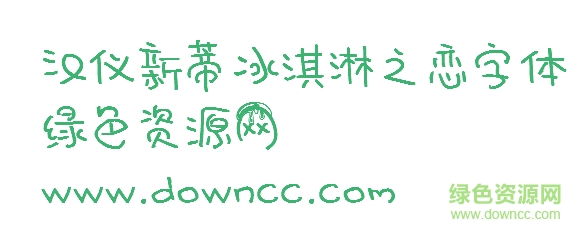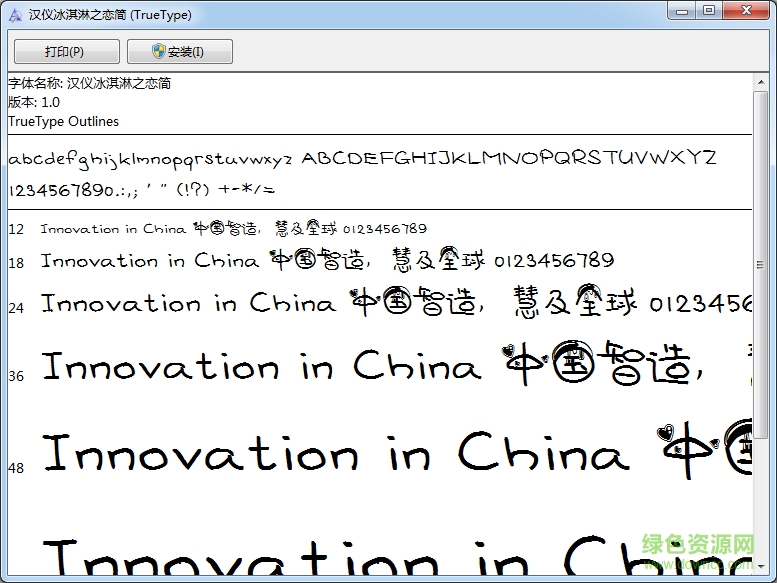
漢儀冰淇淋之戀是一款中文簡寫字體,是一款有著多樣點(diǎn)綴和修飾的個性手寫體,讓文字獨(dú)居審美和活潑特色,感受不一樣的美感,綠色資源網(wǎng)誠意推薦!
漢儀新蒂冰淇淋之戀增加了雪糕和桃心的修飾,是一款觀賞度和閱讀性極佳的藝術(shù)字體,可廣泛運(yùn)用于平面設(shè)計(jì)、海報(bào)設(shè)計(jì)、名片設(shè)計(jì)等場合,歡迎體驗(yàn)!
冰淇淋字體經(jīng)??梢栽?a href="http://kiwanis-srv.org/k/shoujimeihua/" target="_blank">手機(jī)美化教程中看到,字體非??蓯劭ㄍ?。每個字體的點(diǎn)都帶有雪糕的形狀,適用于兒童卡通、創(chuàng)意廣告、藝術(shù)設(shè)計(jì)等場合。